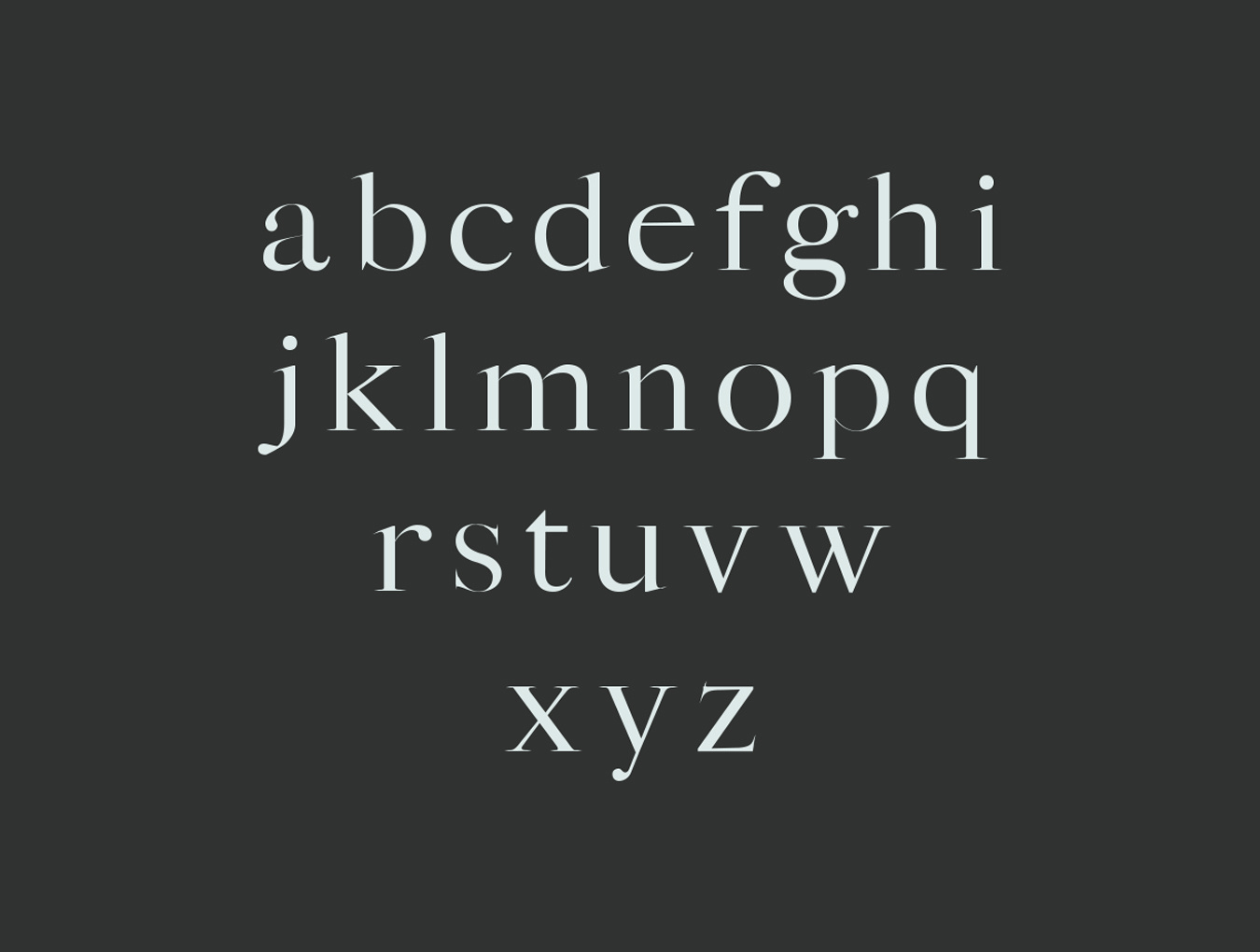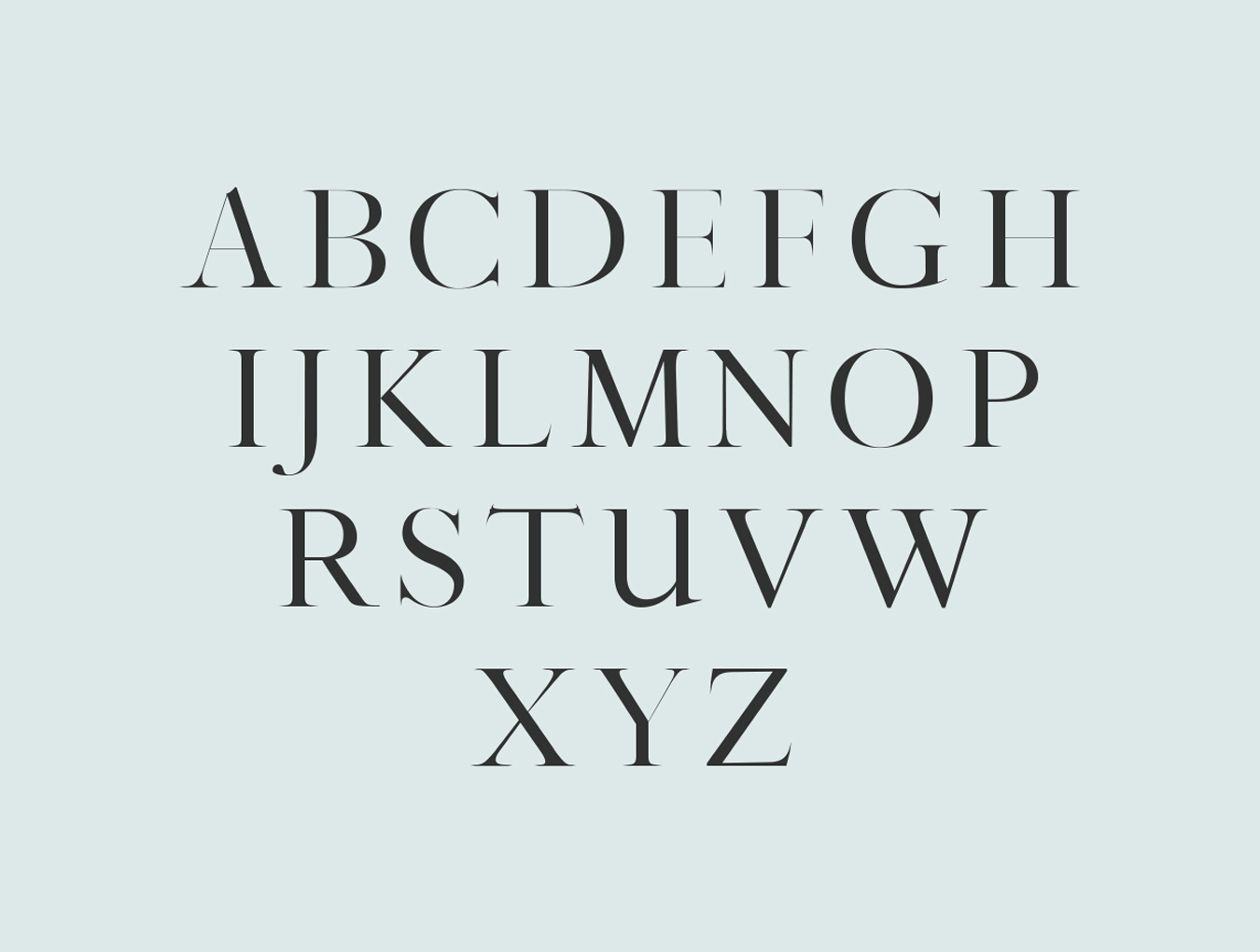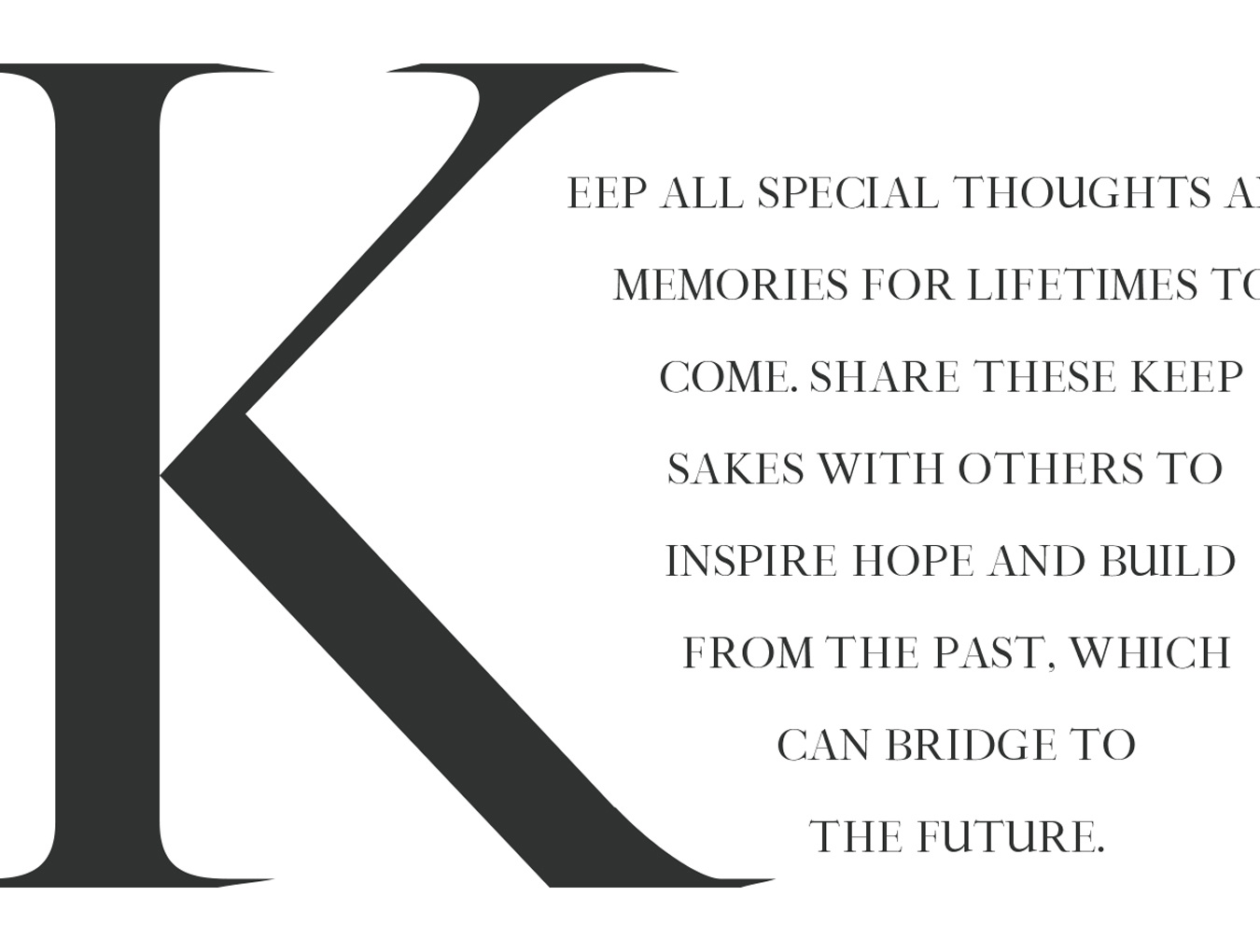
Sharis Serif字体7家庭装,Sharis Serif字体
Sharis Serif Font 7 Family Pack, Sharis Serif Typeface
Sharis Serif字体是一种独特的简洁干净的衬线字体系列,包含7种砝码,Sharis具有独特而现代的衬线外观和感觉。 它非常适合华丽的徽标,标题,网页布局,时尚杂志和品牌。 如果你想尝试一个优雅的外观,它看起来华丽,所有帽子都有宽大的间距,或者在大写字母和小写字母中完美无瑕。